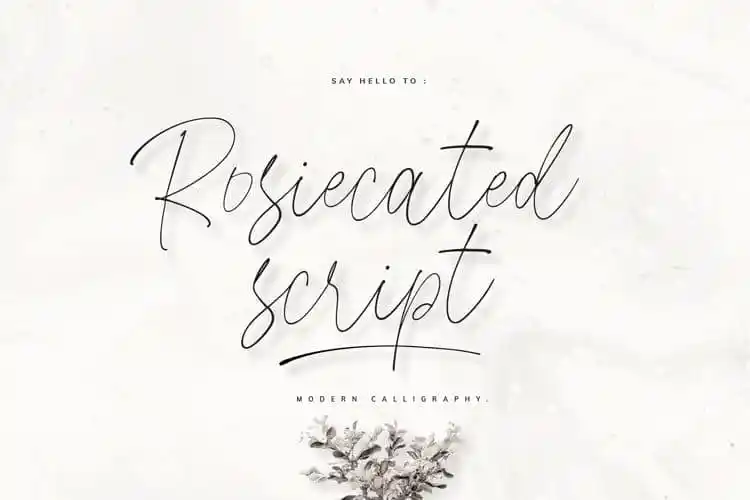
Rosiecated Script Font – Download Grátis
A Rosiecated Script Font é uma elegante fonte cíntica para assinaturas modernas que mantém seu estilo natural e de escrita manuscrita. Ela traz um tipo atraente e sofisticado, com uma personalidade trendy e feminina perfeita para vários tipos de projetos. A Rosiecated Script Font é ideal para fins como cartões de convite de casamento, cartas de gratidão, citações, cards de boas-vindas, logotipos, cartões de visita, festas, formaturas, aniversários, encontros e eventos semelhantes. Ela vem com uma gama completa de letras maiúsculas e minúsculas, um amplo conjunto de pontuação, números e suporte multilíngue, garantindo que sua mensagem seja transmitida de forma clara e atraente em qualquer idioma. A Rosiecated Script Font é certamente o tipo perfeito para tornar seus projetos ainda mais únicos e impecáveis.